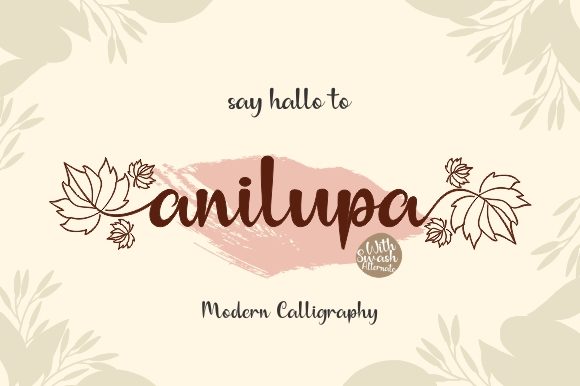
Creativefabrica Anilupa Font
[Creativefabrica] Anilupa Font
Анилупа - это тонкий, элегантный и плавный рукописный шрифт.
Он имеет красивые и хорошо сбалансированные символы, и, как результат, он соответствует широкому кругу дизайнов.
Добавьте его к вашим самым креативным идеям и заметьте, как он делает их живыми!